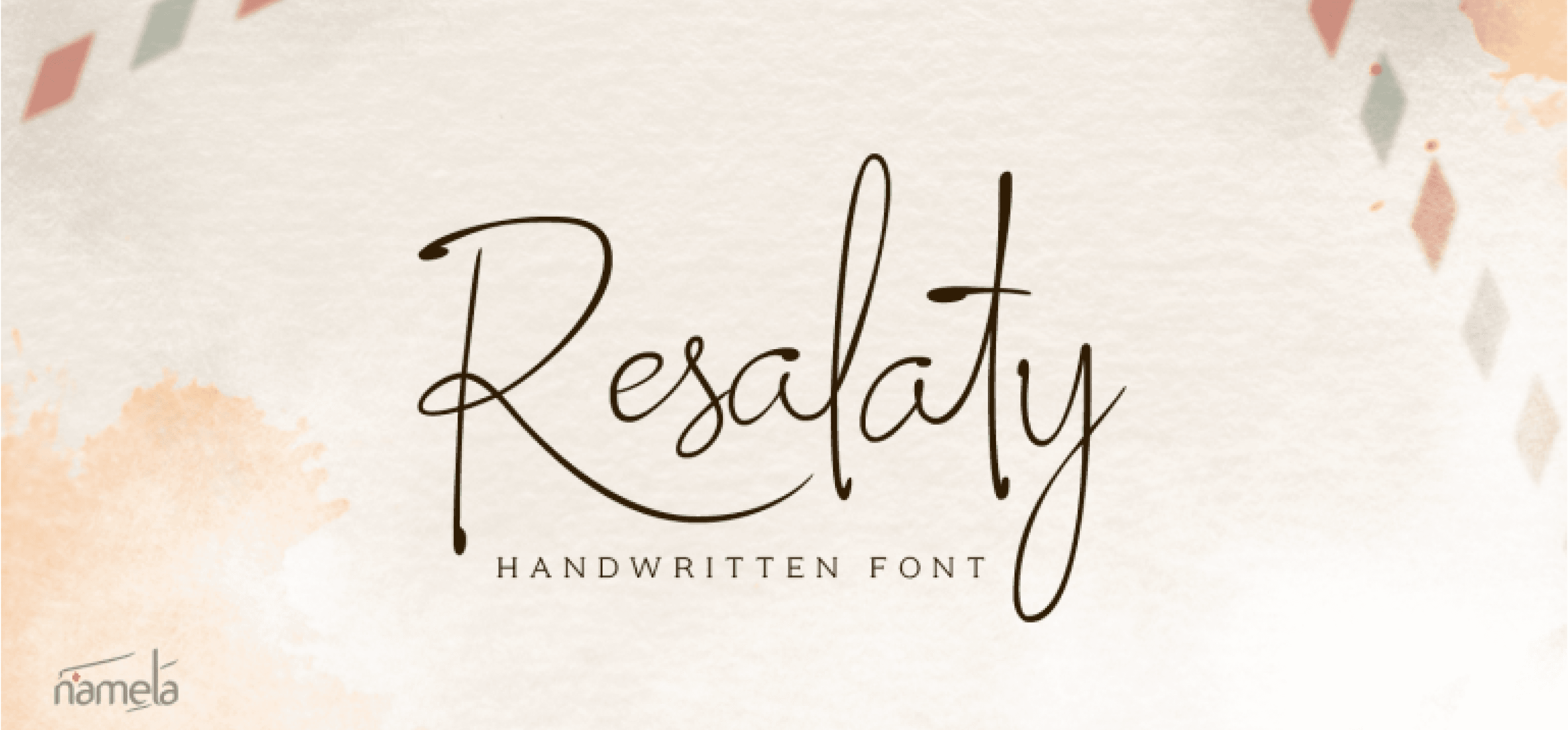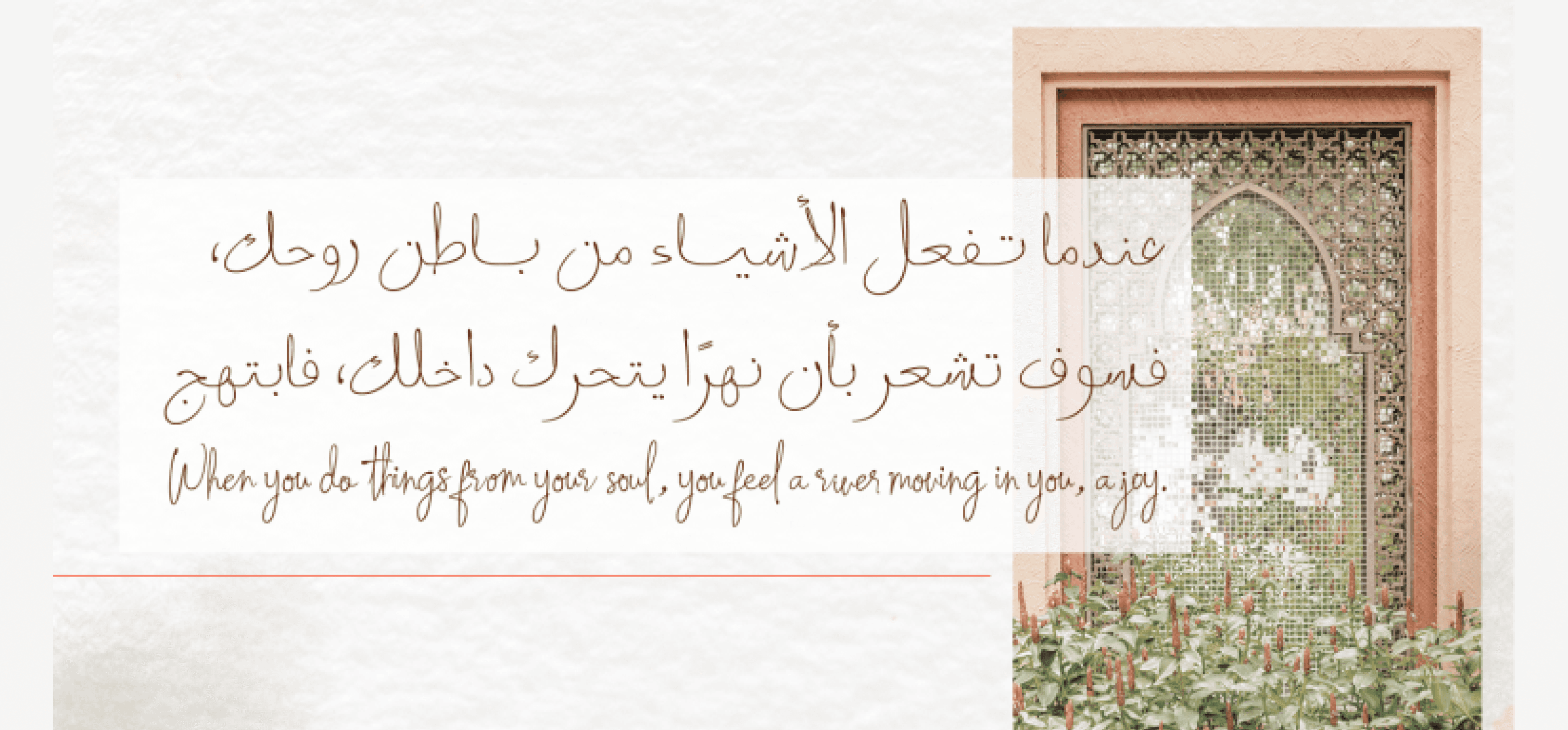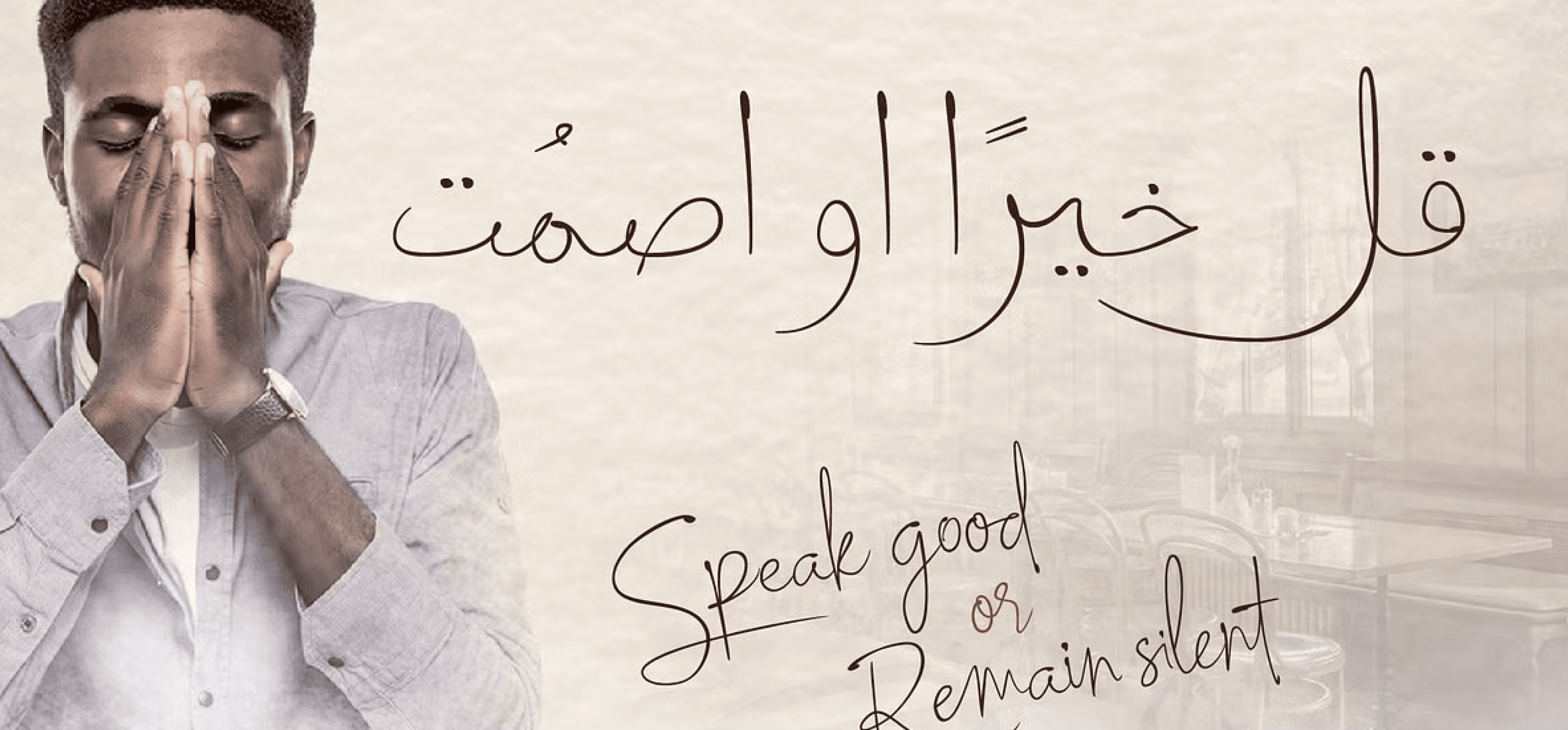
الخط الكتابي (Script Typeface) هو أسلوب خطي متعدد الاستخدامات، يتميّز بقدرته على نقل مشاعر وأجواء مختلفة، تتراوح بين الطابع العفوي، الودود والدافئ، وصولاً إلى الأسلوب الرسمي والراقي.
يلعب نوع أداة الكتابة المستخدمة دورًا أساسيًا في تحديد هذه النبرة، سواء كانت فرشاة، قلمًا حبر، أو أي أداة أخرى، حيث تؤثر بشكل مباشر في أسلوب الحروف وملمسها البصري.